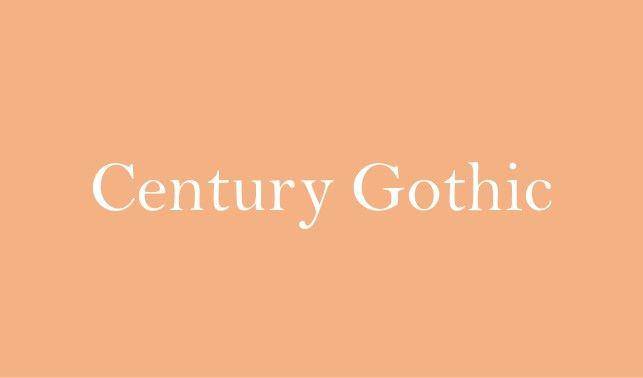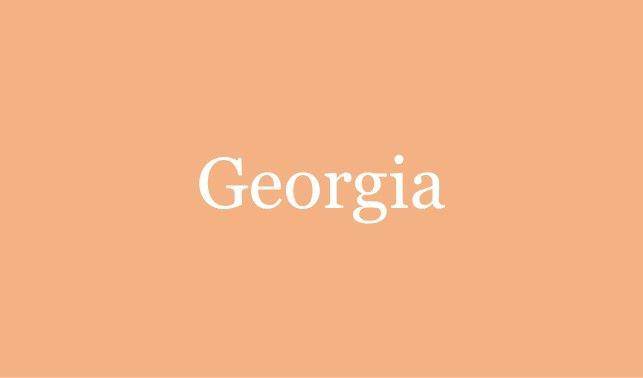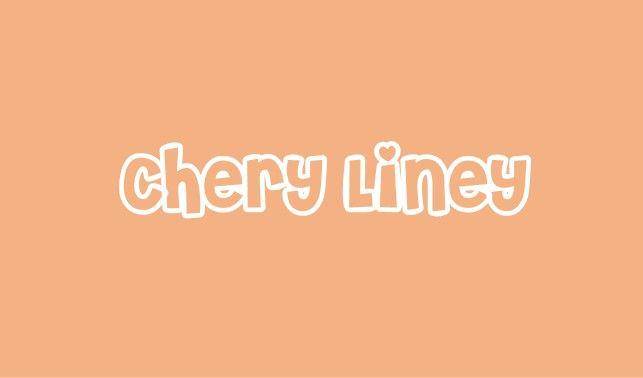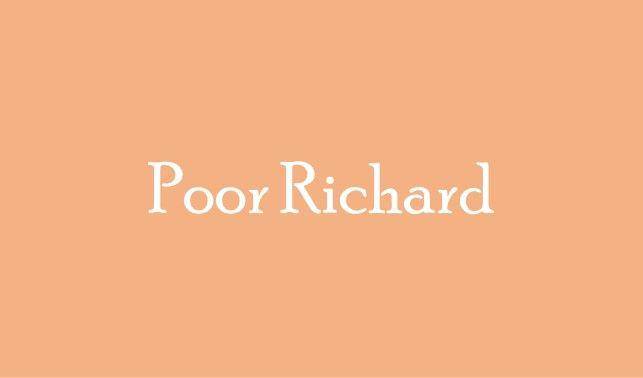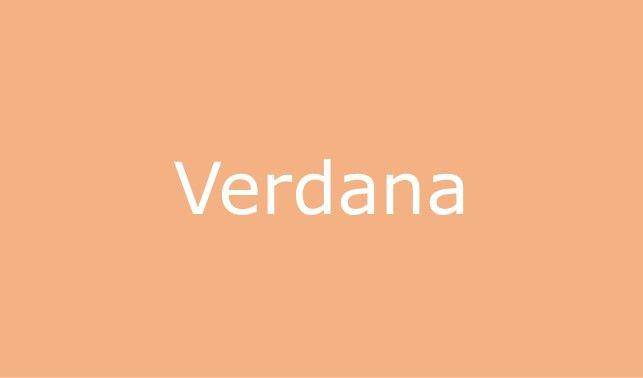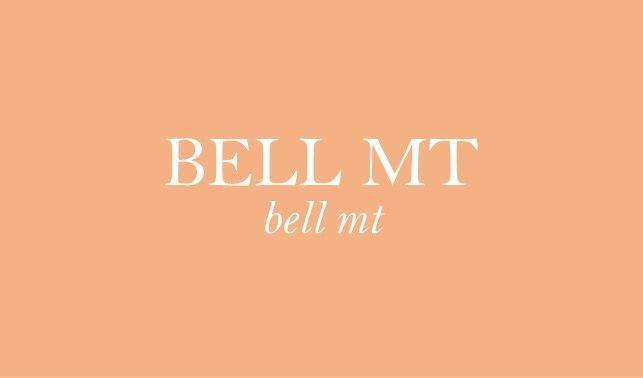
7 Font yang Bagus untuk PPT, Bikin Presentasi Makin Oke
Memilih fon yang tepat untuk slide PowerPoint dapat menunjang kesuksesan presentasi, lho. Oleh karena itu, penting untuk memperhatikan penggunaan dan kombinasinya.
Beberapa font yang bagus untuk PPT bahkan bisa digunakan tanpa perlu mengunduhnya terlebih dahulu. Berikut beberapa font yang bisa kamu gunakan dan gabungkan untuk bikin deck presentasi makin menarik.
Font yang bagus untuk PPT
Jenis fon sendiri terbagi menjadi tiga, yakni serif, sans serif, dan skrip atau yang berbentuk dekoratif. Font serif adalah jenis fon dengan ekor, sedangkan font sans serif berarti tanpa ekor. Adapun fon dekoratif biasanya meniru tulisan tangan.
Tidak ada aturan baku tentang penggunaannya. Selama tulisan terbaca, itu bukan masalah. Kamu pun bisa mengombinasikan keduanya sesuai dengan kebutuhan.
1. Century Gothic
Century Gothic merupakan salah satu jenis huruf sans serif dengan gaya geometris. FYI, font ini dirilis pada 1991 oleh Monotype Imaging dan didasarkan pada Monotype 20th Century.
Bentuk fon ini tegas dan mudah dibaca. Kamu bisa mengombinasikannya sebagai font judul maupun body text.
2. Corbel
Font Corbel dirilis pada tahun 2005 oleh Microsoft. Mirip dengan sebelumnya, fon Corbel juga punya bentuk clean yang tegas. Fon ini dirancang khusus untuk monitor LCD sehingga dapat mengoptimalkan keterbacaan saat presentasi.
Corbel jelas cocok untuk presentasi yang memerlukan kontras. Kamu pun tidak perlu khawatir karena tulisan tetap bisa terbaca walau dari jarak jauh.
3. Georgia
Setelah dua font yang bagus untuk PPT sebelumnya berjenis sans serif, Georgia adalah jenis fon serif. Oleh karena itu, bentuknya memiliki ekor di bagian akhir. Hal ini terlihat pada huruf seperti G, R, I, dan A.
Georgia merupakan fon yang paling mirip dengan Times New Roman. Meski demikian, bentuknya lebih besar sehingga ideal untuk digunakan saat presentasi.
4. Cheri Liney
Font yang bagus untuk PPT berikutnya ada Cheri Liney. Fon ini termasuk jenis dekoratif dengan sentuhan 3D. Bentuknya mirip dengan teks yang biasa digunakan untuk poster atau desain.
Terdapat aksen love sebagai pengganti titik di atas huruf i. Plusnya lagi, font ini bisa tersedia untuk huruf kapital maupun huruf kecil. Hal ini membuat Chery Liney semakin cocok digunakan untuk presentasi, terlebih dalam acara informal.
5. Poor Richard
Poor Richard merupakan fon dengan jenis serif yang memiliki sedikit ekor di bagian belakangnya. Namun, alih-alih memiliki aksen tegas, font ini justru menampilkan kesan klasik yang unik.
Fon Poor Richard tersedia dalam versi huruf kapital maupun huruf kecil. Kamu bisa mengombinasikannya untuk membuat tampilan presentasi jadi lebih ciamik.
6. Verdana
Bisa dibilang, Verdana merupakan salah satu pilihan untuk membuat presentasi yang menarik dan jelas. Fon yang dibuat pada tahun 1996 oleh Mathew Carter ini punya bentuk jelas tanpa aksen mengganggu.
Font Verdana dibuat untuk Microsoft dan dioptimalkan untuk layar sehingga membuat tampilannya semakin jelas. Verdana juga satu dari sekian fon yang kompatibel hampir di semua komputer Windows dan Mac.
7. Bell MT
Bell MT merupakan font yang dipengaruhi oleh karya tipografer Prancis, Fermin Didot. Font ini sangat menarik, terlebih jika digunakan dalam mode italic atau huruf miring. Tulisan akan menjadi lembut, tetapi masih sangat terbaca.
Sebaliknya, saat digunakan dalam huruf kapital tanpa italic, fon ini memberikan kesan tegas yang jelas. Oleh karena itu, Bell MT jadi salah satu font yang bagus untuk PPT di segala suasana.
Font yang bagus untuk PPT di atas akan semakin menarik ketika di-mix and match satu sama lain. Bikin presentasimu makin menarik dan menyenangkan.